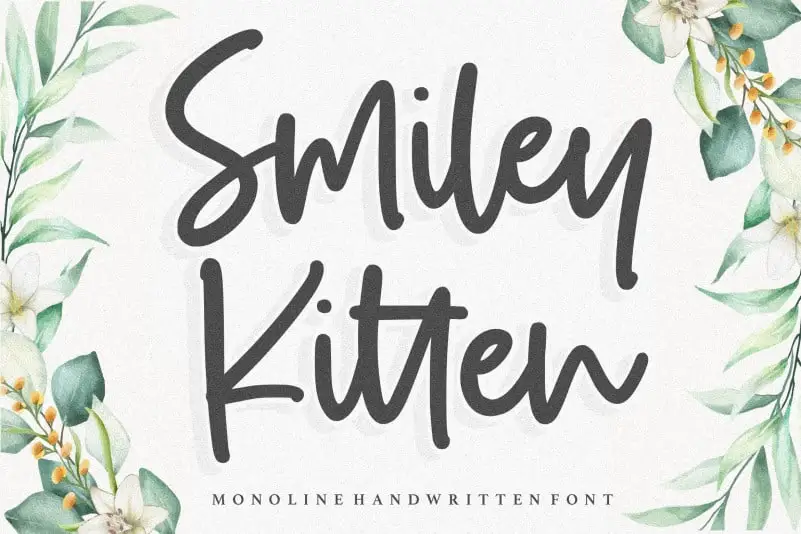
Smiley Kitten Monoline Handwritten Font – Download Grátis
A fonte Smiley Kitten Monoline Handwritten é perfeita para quem procura uma fonte com um toque autêntico e deslumbrante. Suas linhas leves, embutidas em uma caligrafia natural e amorosa, fazem dela uma escolha ideal para estilos de produto como embalagens ou identidade visual de marcas, especialmente quando combinada com outros elementos de design que precisam ser acentuados. Perfeita para um projeto de jornal ou revista moderno, ela é perfeitamente adaptável à temática social media e até mesmo à necessidade criativa para estampas nupciais. Além disso, sua elegância permite que seja usada em qualquer situação onde você precisa expressar frases acima de um fundo, tornando-a uma opção versátil e divertida para designers gráficos. Balpirick é o designer por trás desta fonte única, criando cada traço com cuidado e emoção. Com Smiley Kitten Monoline Handwritten, você ganha não apenas uma fonte elegante e atraente, mas também um ativo visual capaz de dar vida às suas criações digitais, tornando-a um investimento valioso no seu arsenal de ferramentas gráficas.